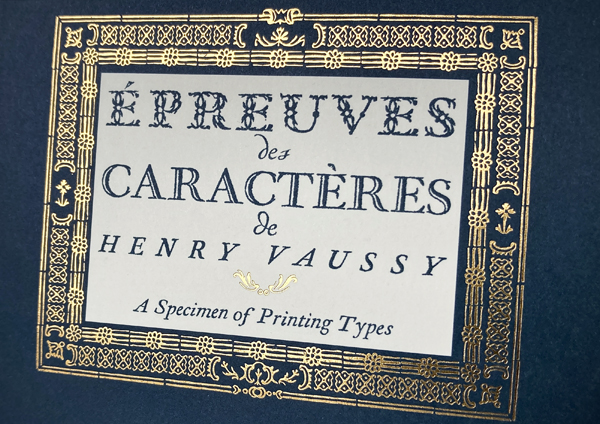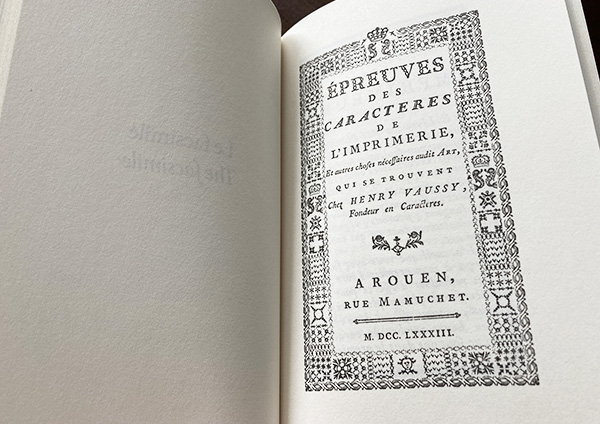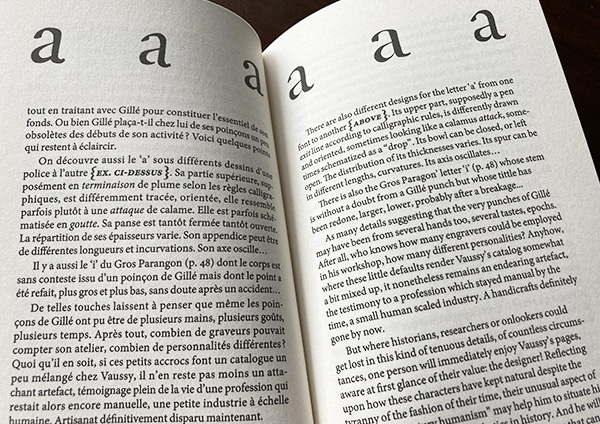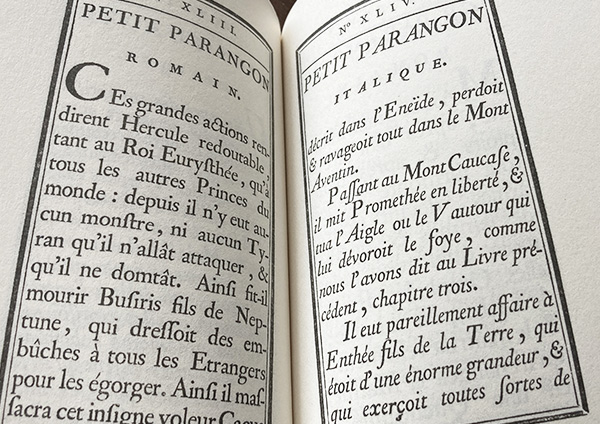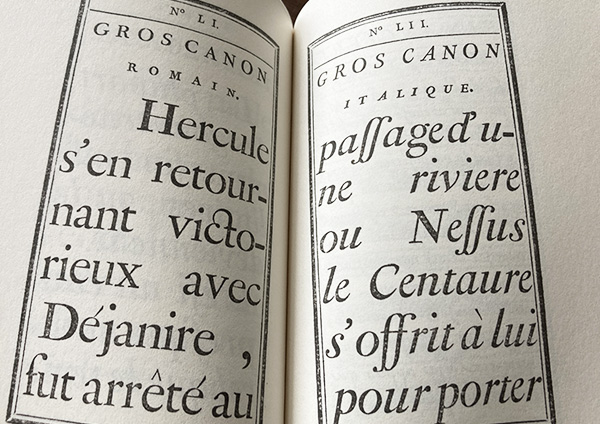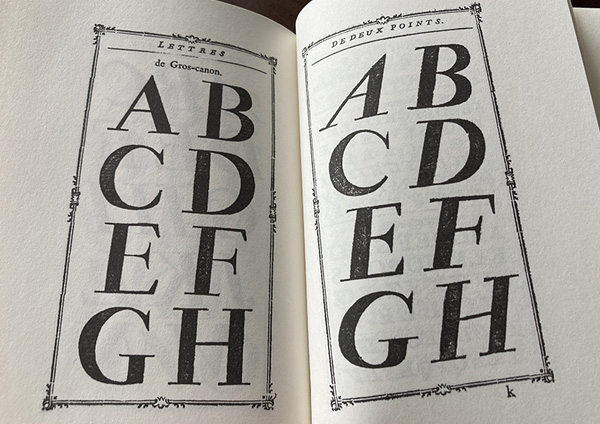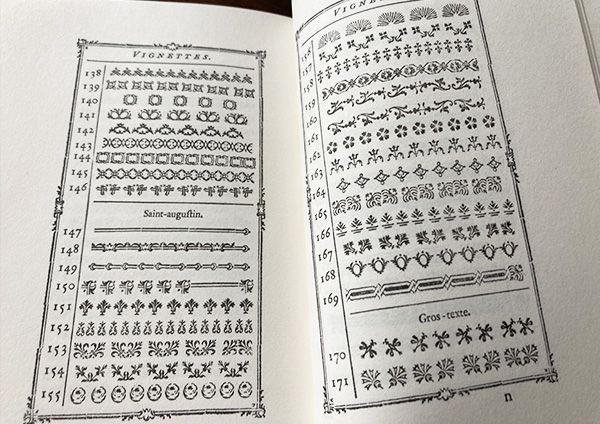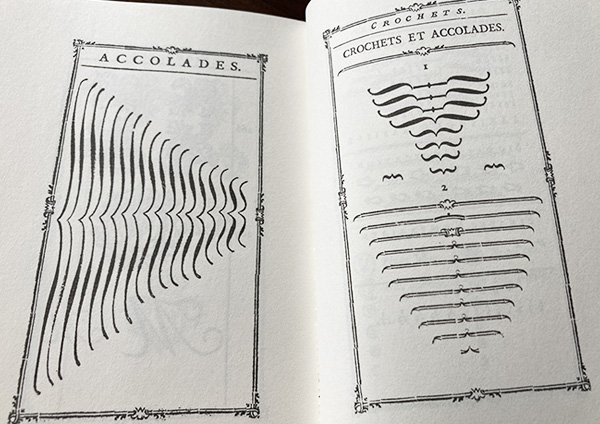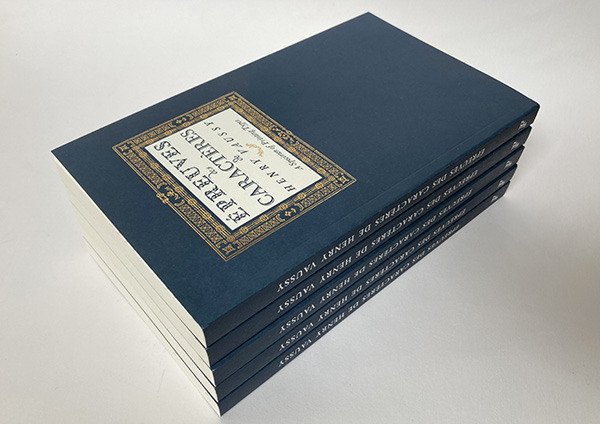
ÉPREUVES DES CARACTÈRES DE HENRY VAUSSY
A Specimen of Printing Types
FACSIMILÉ DU SPÉCIMEN DE 1783 D’UNE FONDERIE TYPOGRAPHIQUE FRANÇAISE MÉCONNUE.
Il s’agit de la première reproduction de ce spécimen rarissime. Chacune des 112 pages a été scannée en très haute résolution sur un exemplaire original, puis nettoyée avec soin mais sans retouche, pour restituer l’exactitude de l’imprimé. Le catalogue de ce fondeur normand contient la vaste palette des polices les plus caractéristiques du XVIIIe siècle. La plupart des caractères s’y avèrent issus de l’atelier d’un important graveur parisien, qui est, lui aussi, étonnamment passé sous les radars de l’histoire jusqu’ici. L’hésitation de leurs dessins entre humanité et technicité nous les fera percevoir en écho à la création d’aujourd’hui.
La note introductive permettra au spécialiste de resituer ces exemples, qu’il pourra confronter à ses propres études. L’amateur pourra quant à lui mieux apprécier ce petit trésor graphique, tout à la fois exemplaire et méconnu.
La dorure qui décore la couverture est un encadrement créé dans le goût de l’époque, à partir d’une dizaine de fleurons du facsimilé.
FACSIMILE OF THE 1783 SPECIMEN OF AN UNKNOWN FRENCH TYPEFOUNDER.
It is the first time this scarce French provincial specimen is reproduced. Each of the 112 page was scanned in very high resolution on an original copy, then carefully cleaned, though without touch-up, to restore the truth of the print. This catalog displays the most significant ranges of very distinctive 18th century’s typefonts. Most of its characters turn out to originate from a noteworthy Parisian engraver’s workshop that has also stangely escaped historians’ scrutiny so far. The hesitancy of their features between humanity and technicality happens to echo today’s design.
The introductory note will allow the type-specialist to contextualize these samples, confront them with his own studies, while the amateur will better understand and enjoy this graphic treasure trove, as more remarkable as it has been disregarded.
The gilded border decorating the front cover page has been created à la mode of the time, from about ten of the facsimile’s flowers.